Peut-être êtes-vous un graphiste à la recherche de la police parfaite pour ajouter une touche visuelle supplémentaire à vos créations. Eh bien, vous avez de la chance ! Dans cet article, nous explorerons les 18 meilleures polices de pizza qui propulseront vos créations à un tout autre niveau.
Si vous êtes graphiste, vous connaissez l'importance de sélectionner la bonne police pour vos projets. Cela peut faire ou défaire la conception globale et l’impact de votre travail.
Ainsi, lorsqu'il s'agit de designs sur le thème de la pizza, l'utilisation de la bonne police peut transmettre instantanément le délice et le plaisir associés au plat préféré de chacun. Dans cet article, nous avons dressé une liste des 18 meilleures polices de pizza qui vous aideront à y parvenir !
Des polices audacieuses et volumineuses rappelant des tranches de pepperoni aux polices ludiques et manuscrites qui capturent l'essence d'une pizzeria, nous avons ce qu'il vous faut. Ces polices ont été soigneusement sélectionnées pour offrir une variété de styles et d'ambiances, garantissant que vous trouviez la solution idéale pour votre projet.
Ainsi, que vous conceviez un menu pour une pizzeria locale, que vous créiez des publications sur les réseaux sociaux sur le thème de la nourriture ou que vous travailliez sur un logo sur le thème de la pizza, ces polices sauront certainement faire ressortir vos créations et laisser une impression durable.
Dans cet article, nous présenterons chaque police avec des exemples et partagerons des conseils sur la façon de les intégrer efficacement dans vos conceptions. Prêt à faire passer vos projets sur le thème de la pizza au niveau supérieur ?
Plongeons-nous et découvrons les 18 meilleures polices de pizza qui rendront vos créations irrésistiblement délicieuses !
Meilleures polices de pizza premium
Vous cherchez à ajouter une touche de gourmandise à vos projets de design ? Ne cherchez pas plus loin que notre sélection des meilleures polices de pizza premium ! Ces polices alléchantes élèveront vos créations à un tout nouveau niveau de bonté ringarde.
Alors pourquoi attendre ? Plongez et découvrez la police parfaite pour votre prochain projet – vos créations vous remercieront !
Couleur de la pizza
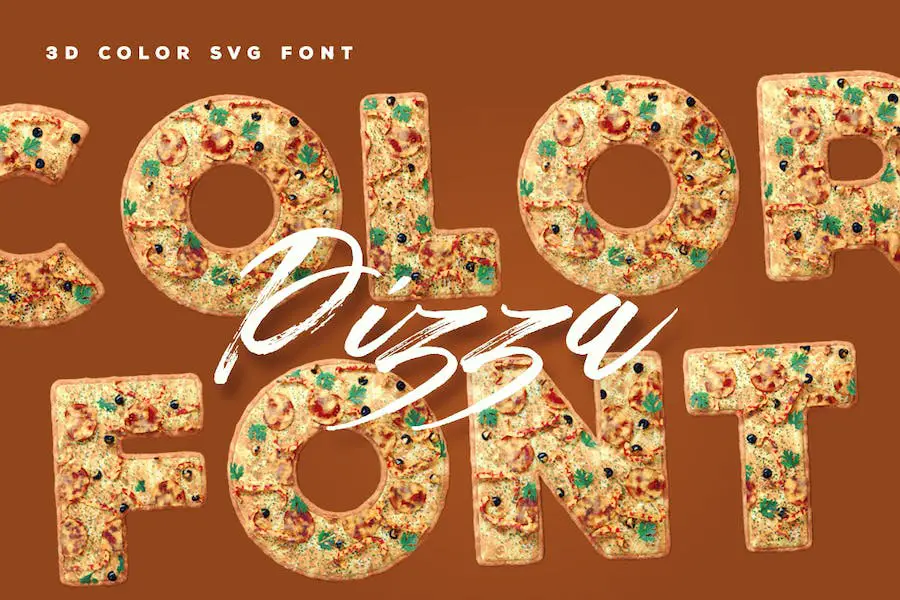
Pizza Color est une police unique qui ajoute une touche de couleur et de plaisir à vos projets de conception. Il s'agit d'une police SVG de type ouvert, ce qui signifie qu'elle fonctionne parfaitement dans Photoshop CC 2017+, Illustrator CC 2018 et même certaines applications Mac.
Cette police est parfaite pour les graphistes qui souhaitent agrémenter leurs projets d'une touche ludique et vibrante. Que vous conceviez un menu, un logo ou un dépliant promotionnel pour une pizzeria, Pizza Color fera vraiment ressortir vos créations.
Avec Pizza Color, vous avez la possibilité d’incorporer des couleurs alléchantes directement dans votre texte. Cette police vous permet d'ajouter des dégradés et de la texture à chaque lettre, créant ainsi un effet accrocheur et appétissant.
Fini les polices ennuyeuses en noir et blanc – Pizza Color donne vie à votre texte avec une délicieuse touche.
Pizza affamée
Hungry Pizza, une police qui ajoute de la saveur à vos créations. Cette nouvelle police polyvalente est parfaite pour le logo de votre entreprise, de vos aliments et boissons ou de votre restaurant. Avec son style unique, il apporte une touche fraîche et gourmande à vos projets.
Ses attributs incluent un design épuré et moderne, le rendant facile à lire et accrocheur. Les formes de lettres soigneusement conçues donnent un sentiment d'authenticité et de professionnalisme à votre travail. Hungry Pizza est le choix idéal pour les menus, la signalisation, les emballages et bien plus encore.
Cette police est conçue dans un souci de polyvalence. Il est disponible dans une variété de poids et de styles, vous permettant de créer différentes ambiances et ambiances. Des titres audacieux et percutants au corps de texte élégant et sophistiqué, Hungry Pizza a ce qu'il vous faut.
Pizza Voyage
Pizza Travel est une police hilarante qui présente un design de lettre unique en son genre. Avec son style décalé, il apporte une touche amusante et unique à tout projet de design.
Les formes de lettres ludiques et distinctes de la police la rendent parfaite pour ajouter une touche fantaisiste à vos créations graphiques. Que vous travailliez sur une affiche sur le thème de la pizza, un menu de restaurant ou même une invitation à une soirée pizza, Pizza Travel fera certainement ressortir votre design.